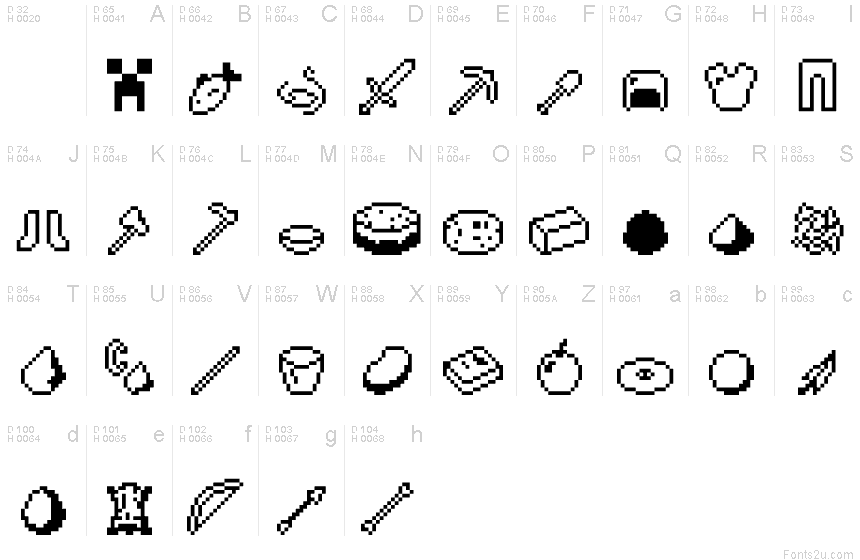
Craft Regular
Pour les fans de Minecraft voici un font tant recherch ^^ bien sur il n'est pas complet mais cette version comporte tout les lments essentiel dont les objets et autres matire du jeu ainsi que pour le plaisir un symbole CREEPER !
(la plupart sont en MAJ et impeu du reste en Min )